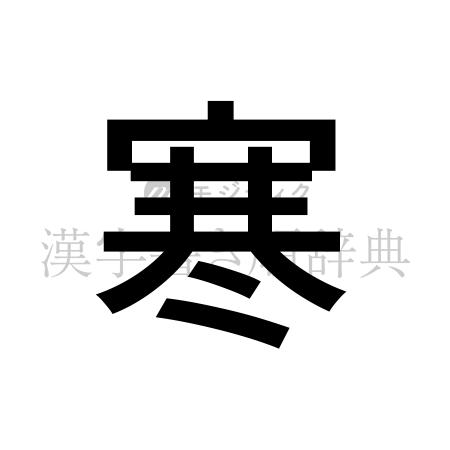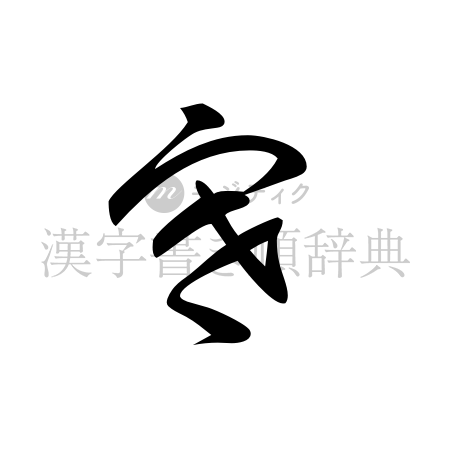
漢字「寒」(カン)の書き順・読み方・意味・部首・画数
「寒」の書き順動画アニメーション(12画)
「寒」の書体
• 寒の書体「ゴシック体」のイメージ
• 寒の書体「明朝体」のイメージ
• 寒の書体「教科書体」のイメージ
• 寒の書体「楷書体」のイメージ
• 寒の書体「行書体」のイメージ
• 寒の書体「草書体」のイメージ
• 寒の書体「隷書体」のイメージ
• 寒の書体「篆書体」のイメージ
「寒」の意味
• 冷たい。
• 冷え込む。
• 冬の季節。
• 寒さ。
• 寒気。
• 寒冷。
• 寒村(さびれた村)。
• 寒色(冷たい感じの色)。
• 寒心(心が冷えること)。
漢字は1文字で多様な意味を持ちますが、「寒」を英語で表す場合、一般的には cold などがあります。
「寒」の成り立ち・由来
六書分類 会意文字
構造 宀(家)+茻(敷きつめた草)+人+冫(氷)
「寒」は複数の要素を組み合わせた会意文字です。上部の「宀」は家屋を表し、その中に人がいる様子を描きます。人の周りには「茻」すなわち枯れ草を敷きつめた形が置かれ、下部の「冫」は氷を示しています。すなわち、寒い冬に家の中で人が草をまとって寒さをしのぎ、足もとには氷が張っているさまを表現し、「さむい」「冷える」という意味を生み出しました。現在の字形は上部が「三」や「八」の形に整えられていますが、もとは草を敷いた様子を写したものです。
※ 下部を氷(冫)とみる説のほか、両手を表すとする解釈など細部には諸説があります。
寒色 - かんしょく
寒い感じを与える色。
寒心 - かんしん
恐ろしいことに遭い、ぞっとすること。
寒冷 - かんれい
冷たく寒いこと。温暖。
「寒」の構成部品
「寒」は上に「宀(うかんむり)」、下に「三(み・サン)」「八(はち)」「冫(にすい)」を組み合わせた漢字です。